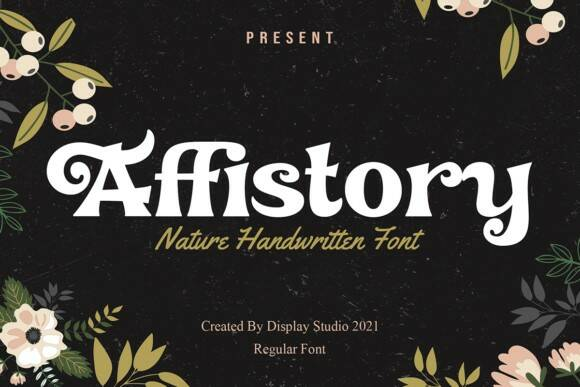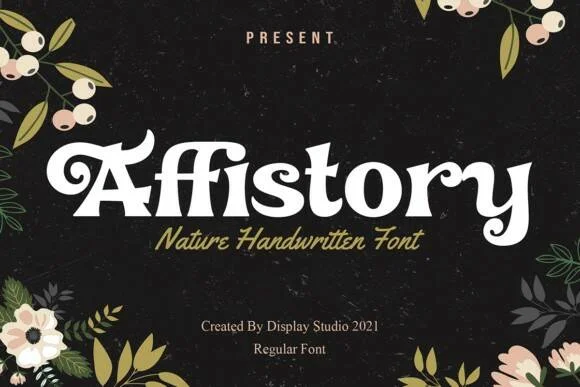
[Creativefabrica] Affistory Font (2021)
Название: Affistory Font (2021)
Affistory - это красивый и стильный рукописный шрифт, который идеально подходит для создания логотипов брендов, приглашений, поздравительных открыток или любых других проектов, которые вы задумали. Смело добавляйте его в свои творческие проекты, и он подчеркнет красоту вашей работы!